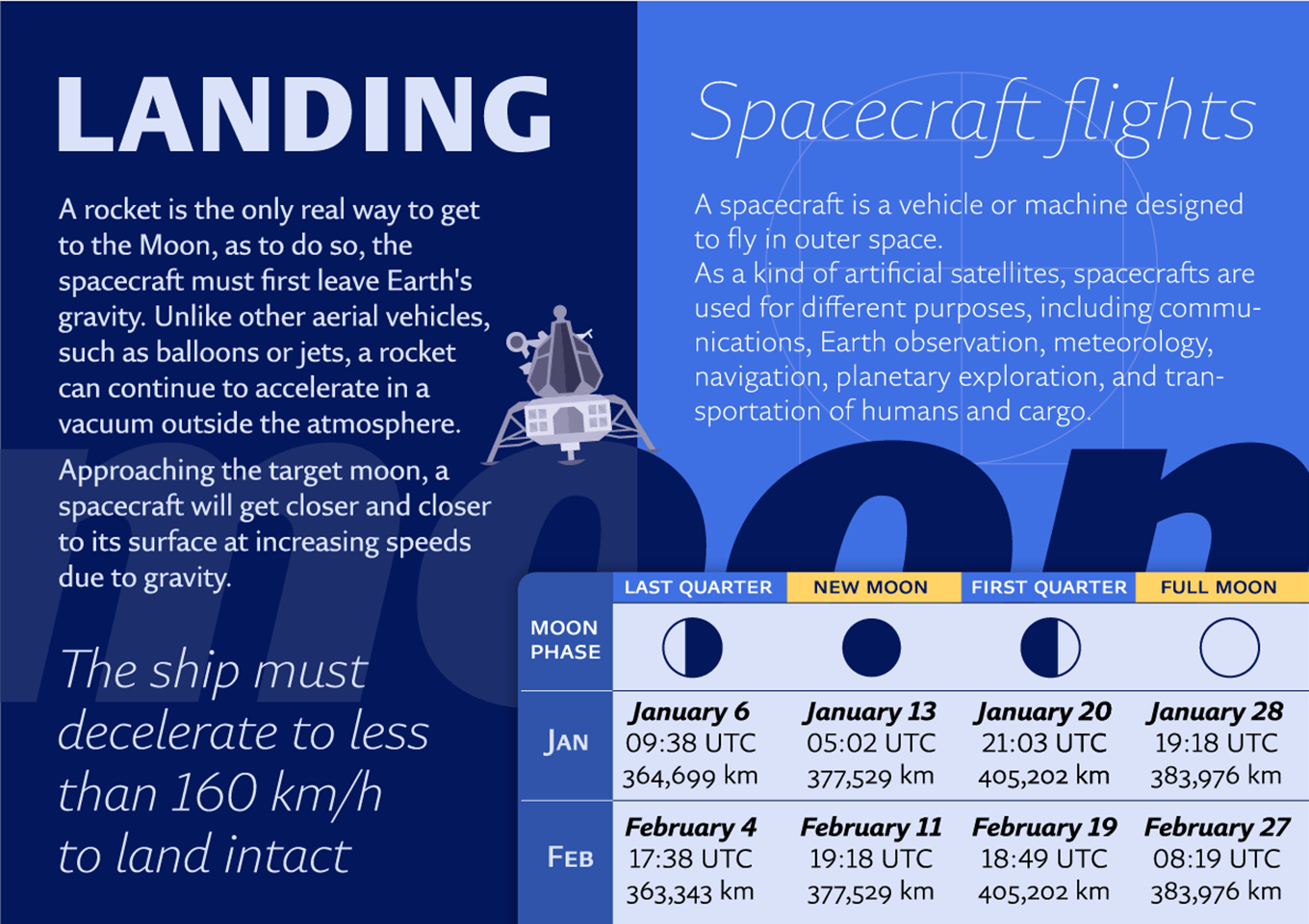
Roleは 、セリフ、サンセリフ、スラブセリフ、ソフト(ラウンデッド)の4つのスタイルと、Text(本文用)、Display(小見出し用)、Banner(大見出し用)の3つのサイズ別に最適化されたバリエーションを持つ、合計200書体のスーパーファミリー書体です。すべての書体は、「誠実さ」と「安定感」をコアイメージとし、Sansは「クリーン」をテーマに制作されています。 Role Sans Textはコントラストを抑えた可読性の高い本文用書体です。